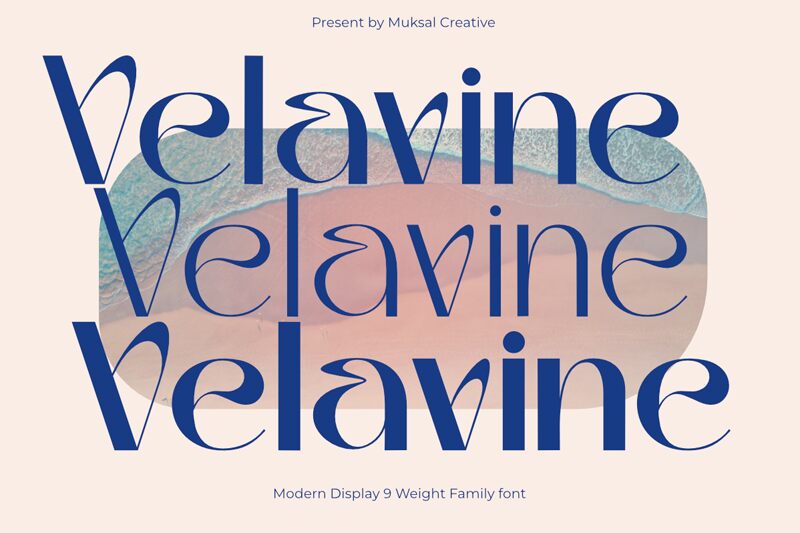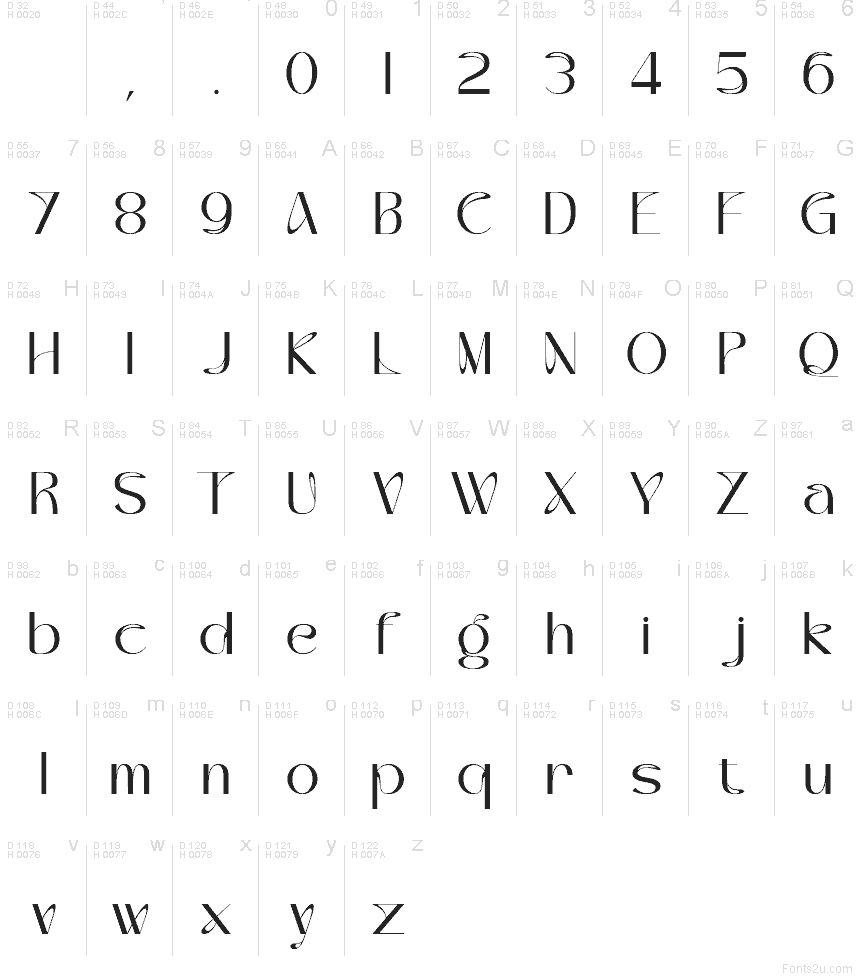
Velavine od studia Muksal Creative je bezplatný retro font typu display, který vyniká dlouhými, zužujícími se křivkami obtékajícími robustní svislé formy. Tento kontrast dodává písmu vysoký, módní rytmus, díky němuž každý znak působí protaženě a sebejistě, nikoliv jen dekorativně.
Skvěle se hodí pro branding butiků, obaly kosmetiky, menu restaurací, obaly alb a plakátové titulky, které vyžadují vytříbený vintage nádech. Protáhlé křivky a úzké vnitřní prostory dávají krátkým slovům záměrně stylizované tempo, takže font mnohem lépe vynikne v nadpisech, logách a dalších krátkých textových celcích než v běžném odstavci.
Prezentace a vizuální ukázka písma Velavine Regular
Mapa znaků písma Velavine Regular
Mapa znaků písma Velavine Regular: Základní latinka, strana 1
Glyfy písma Velavine Regular — Základní latinka, strana 1